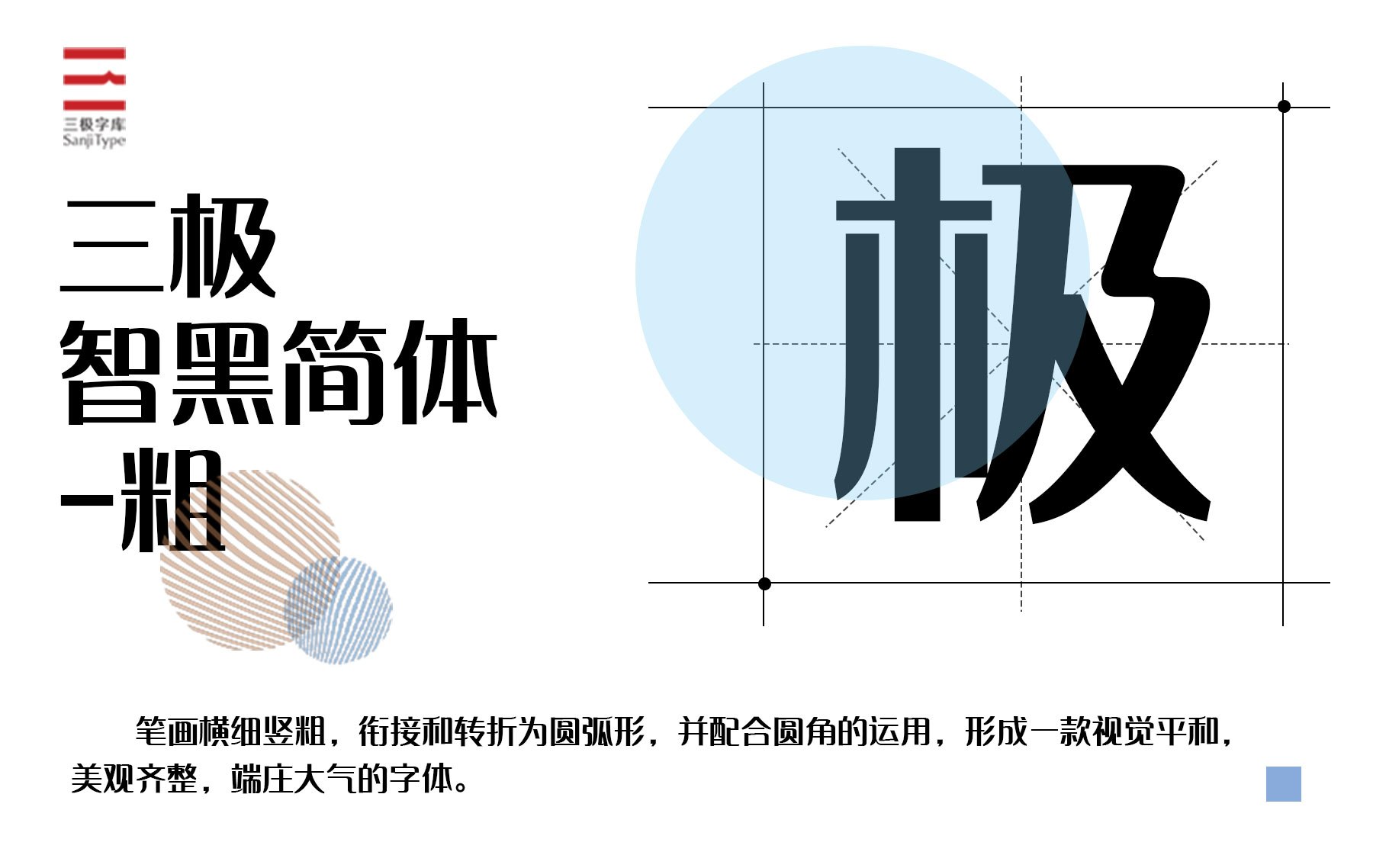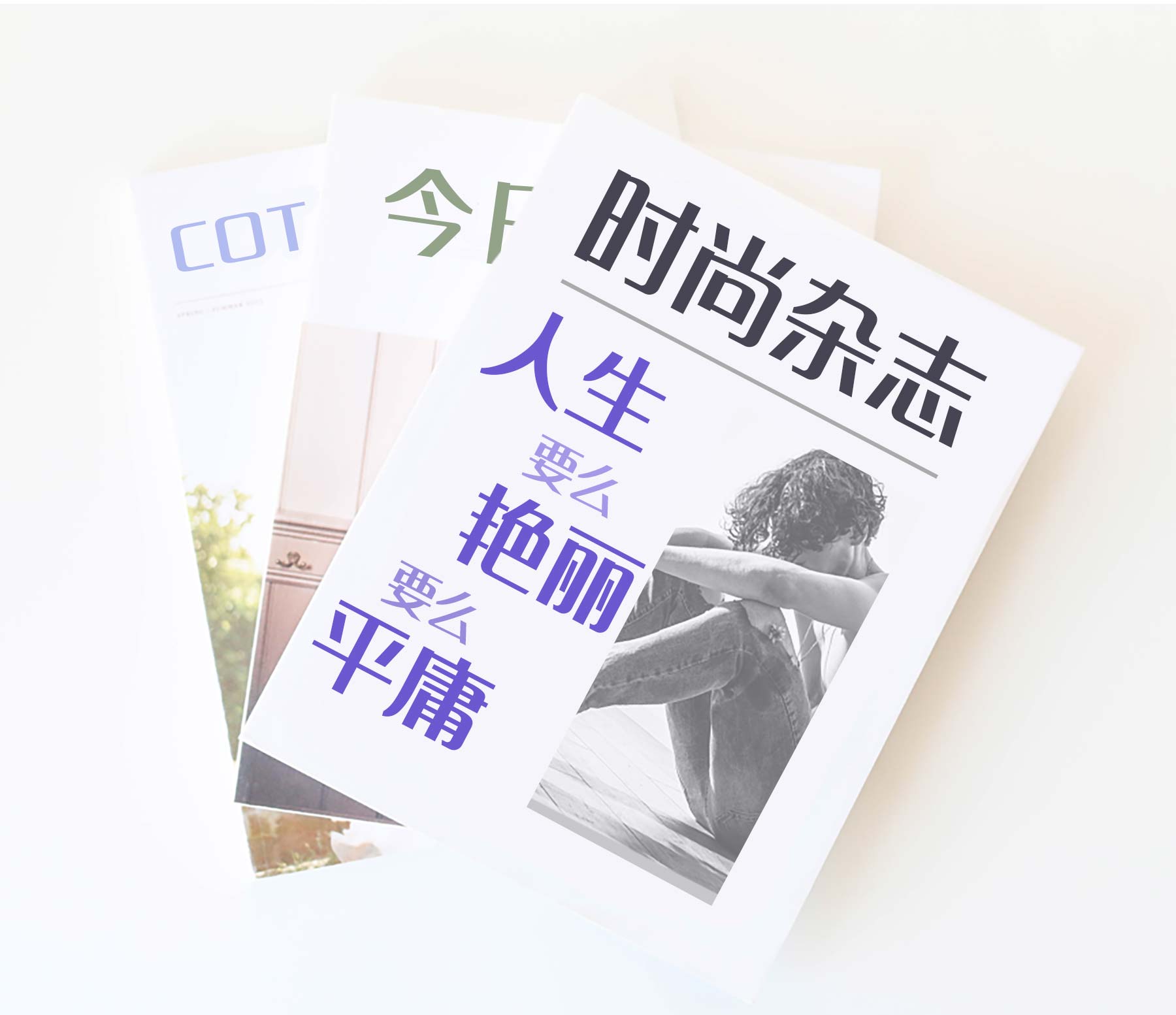
三极智黑简体-粗
去小智而大智明
曾南
三极智黑简体是一款家族字体,笔画横细竖粗,既有方块字的挺拔气势,又在字体衔接处加入圆角,带出柔和婉转质感,形成一款美观齐整,端庄大气的字体。适用于杂志标题、品牌广告和产品包装的设计。
同时适用于大众媒介中,包括杂志、书籍、广告、标志、宣传册、包装、影视、动漫、交互设计等。